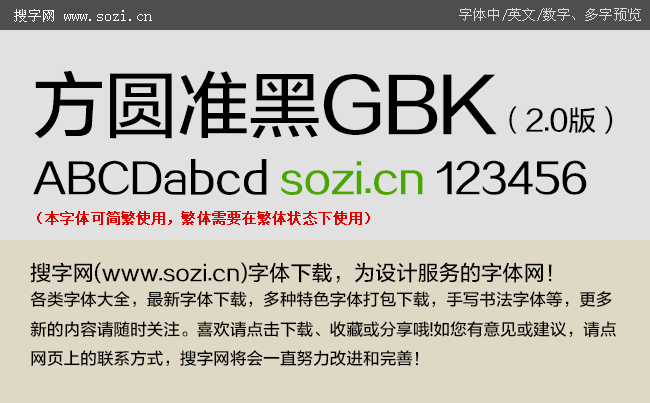
方圓準(zhǔn)黑GBK
搜字網(wǎng)提供一款方圓準(zhǔn)黑GBK下載,方圓準(zhǔn)黑是一款標(biāo)準(zhǔn)的中黑字體,該字體端正大方,識別性強,整體風(fēng)格出色,且GBK標(biāo)準(zhǔn)收錄文字更全,適用于廣告設(shè)計、名片設(shè)計、包裝印刷、產(chǎn)品設(shè)計等應(yīng)用。